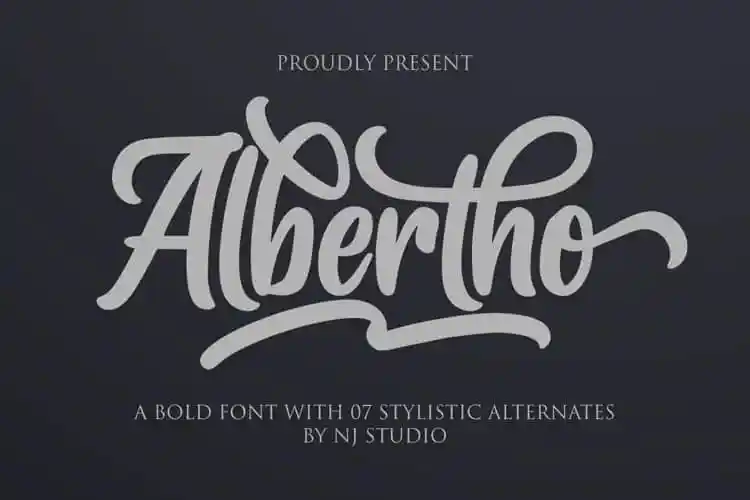
A fonte Albertho Script Font é uma tipografia script com estilo elegante de escrita a mão romântica. Ela é ideal para quem procura fontes adequadas à arte manual para projetos DIY, transformando qualquer ideia criativa em verdadeiros trabalhos de arte únicos e incríveis. Desenvolvida pelo designer NJ Studio, esta fonte possui versões leves e bold, feitas especialmente para variados tipos de designs vectoriais, impressão, como convites de casamento digitais, blogs, lojas online, mídia social. A impressão também pode ser utilizada em diversas aplicações, desde roupas e acessórios até logotipos e cartões de visita. Albertho Script Font é uma escolha perfeita para aqueles que buscam uma fonte elegante e romântica para enriquecer suas criações. Seja você um designer gráfico, criador de blogs ou simplesmente alguém que adora criar, este design elegante vai tornar sua arte ainda mais única e inovadora.